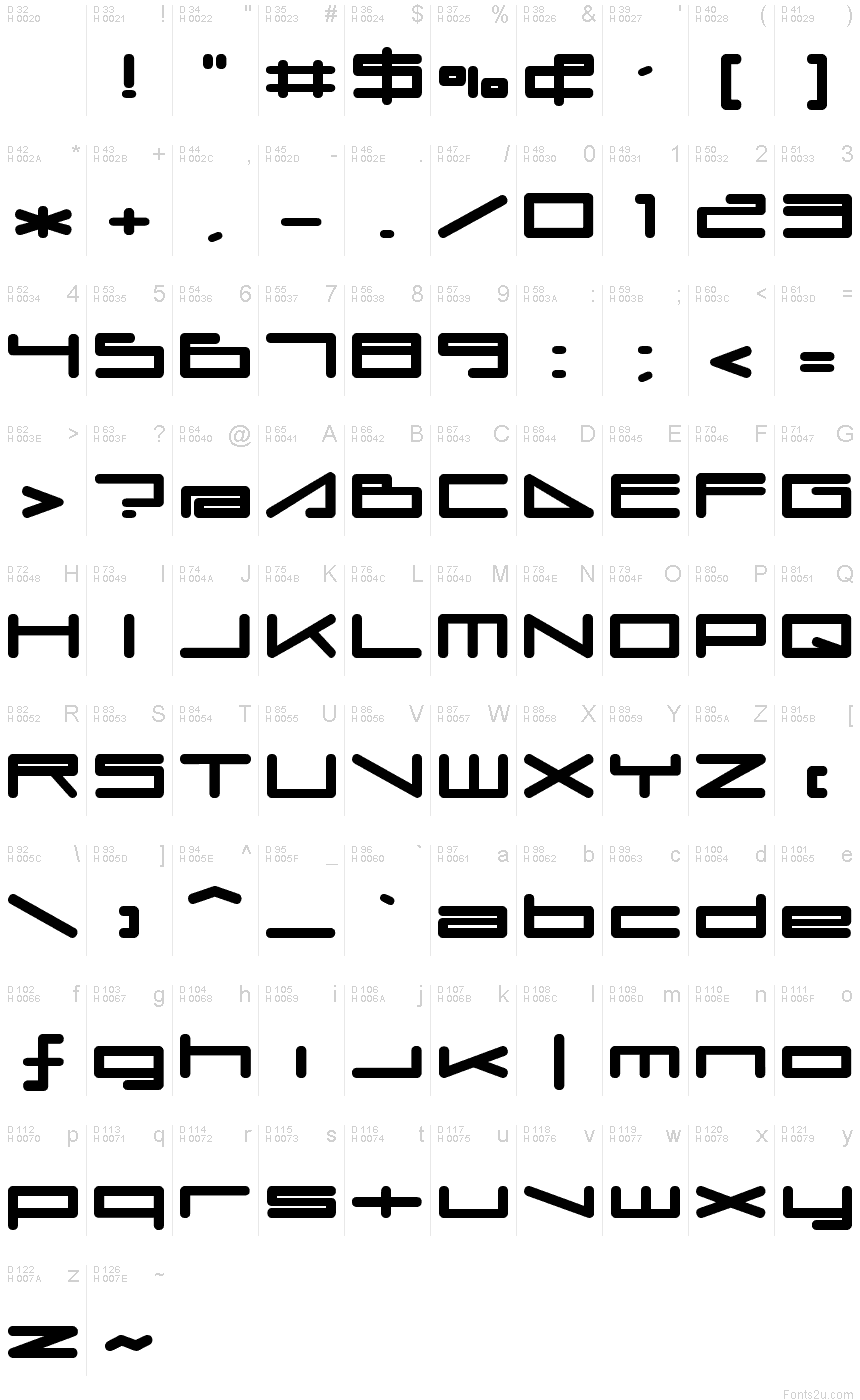
Umop Medium to darmowy, techniczny krój pisma typu display o miękkim, modularnym rytmie. Litery wyglądają, jakby zostały zbudowane z zaokrąglonych prostokątnych torów i głębokich zakrętów w kształcie litery U, co nadaje temu fontowi niski, elektroniczny wygląd, balansujący gdzieś pomiędzy wczesnym brandingiem cyfrowym a retro-futurystyczną grafiką interfejsów.
Naturalnie sprawdza się na ulotkach muzycznych, w logotypach gier, tytułach plakatów, ekranach startowych aplikacji i opakowaniach, wszędzie tam, gdzie kompaktowy napis potrzebuje maszynowego tonu, ale bez ostrości czy agresji. Jako darmowy font, doskonale nadaje się również do krótkich haseł na okładkach i tytułów, ponieważ dzięki szerokim poziomym formom i zapętlonym łukom, nawet krótkie słowo sprawia wrażenie ręcznie zaprojektowanego napisu.